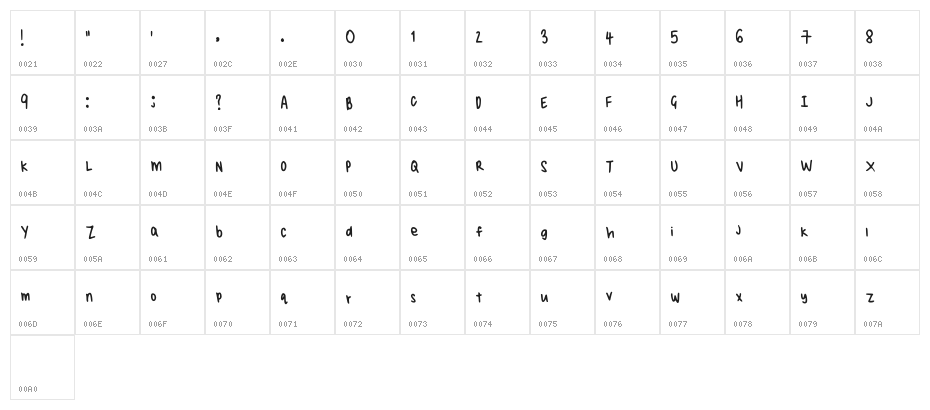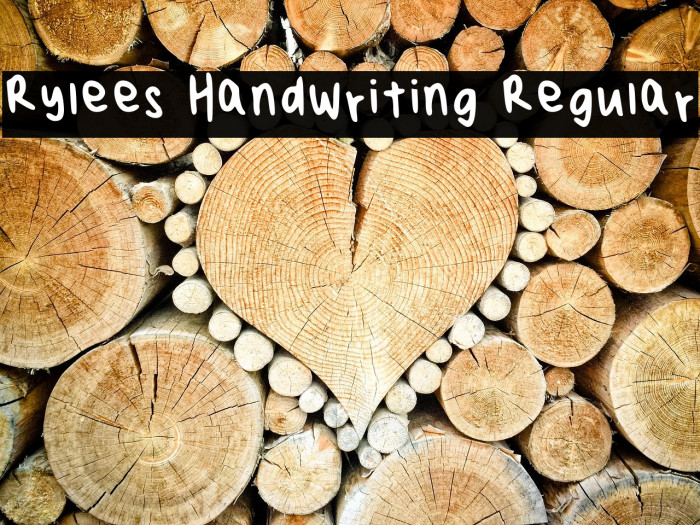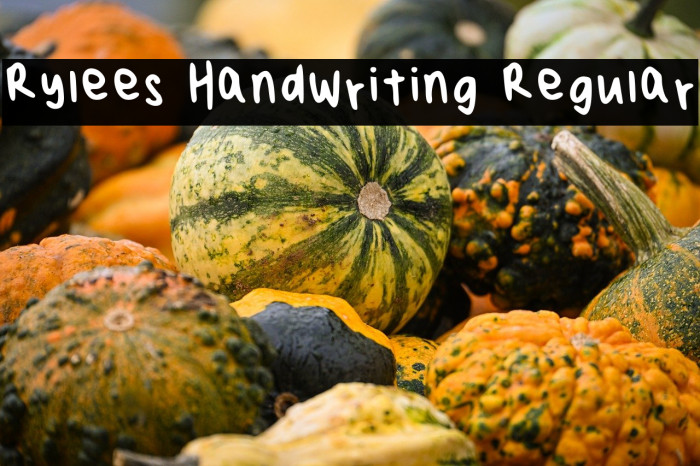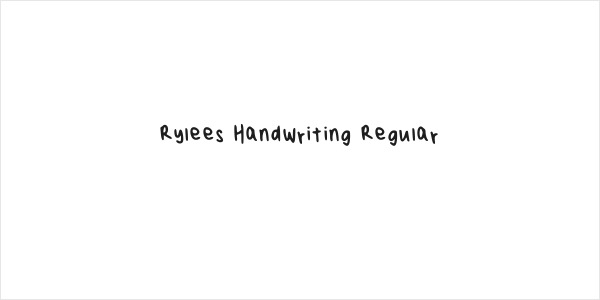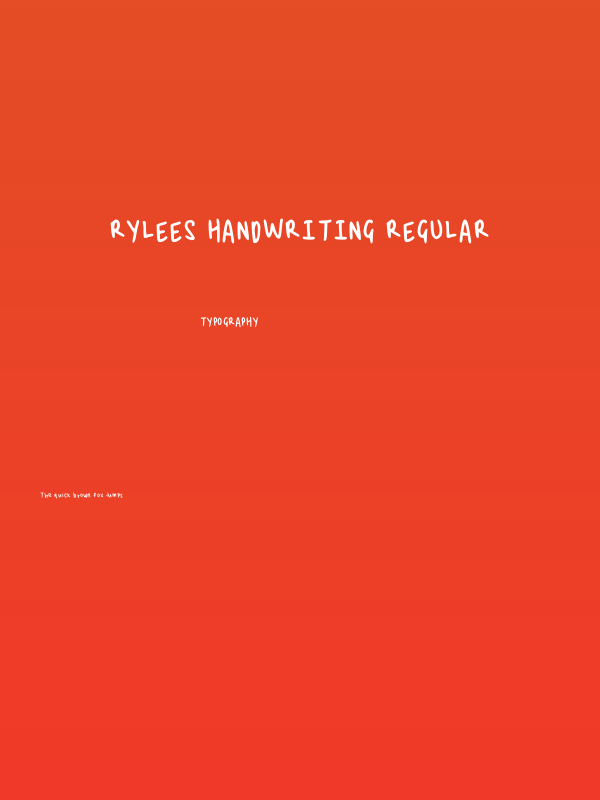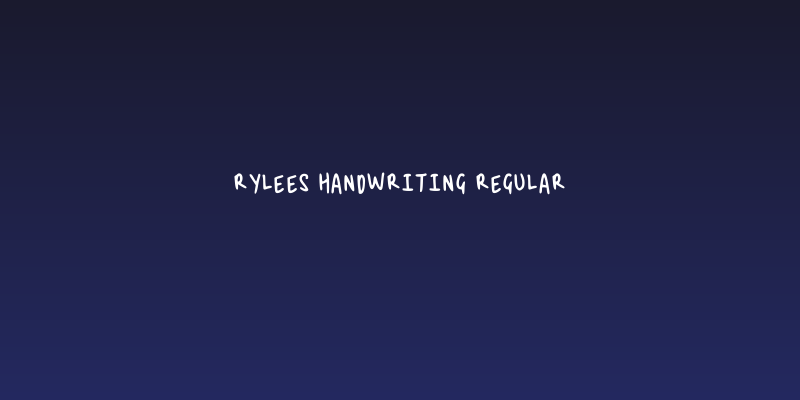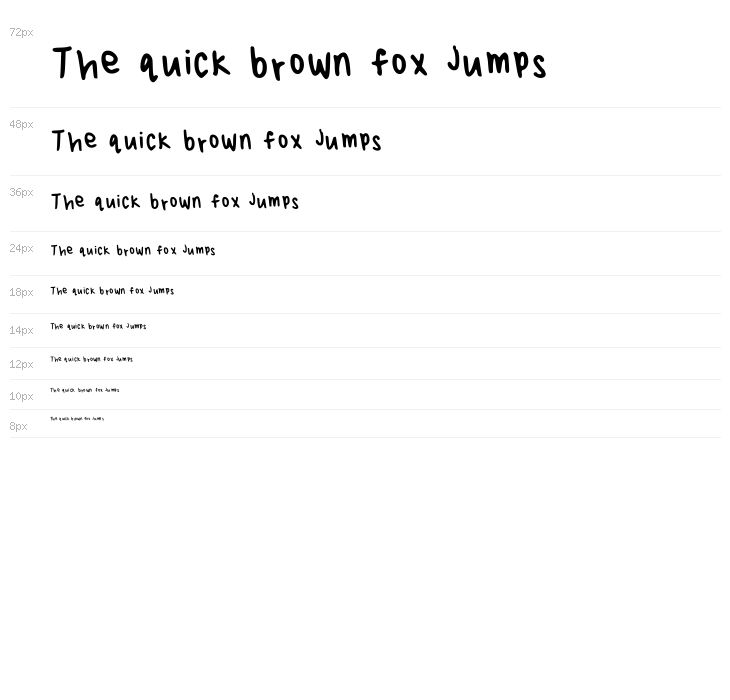
Rylees Handwriting Regular Font
| Stile generale | Casual, Playful |
| Caso d'uso | Headlines, Informal text, Creative projects |
| Progetti proposti | Ideal for personal invitations, greeting cards, informal branding, and creative projects that require a handwritten touch. |